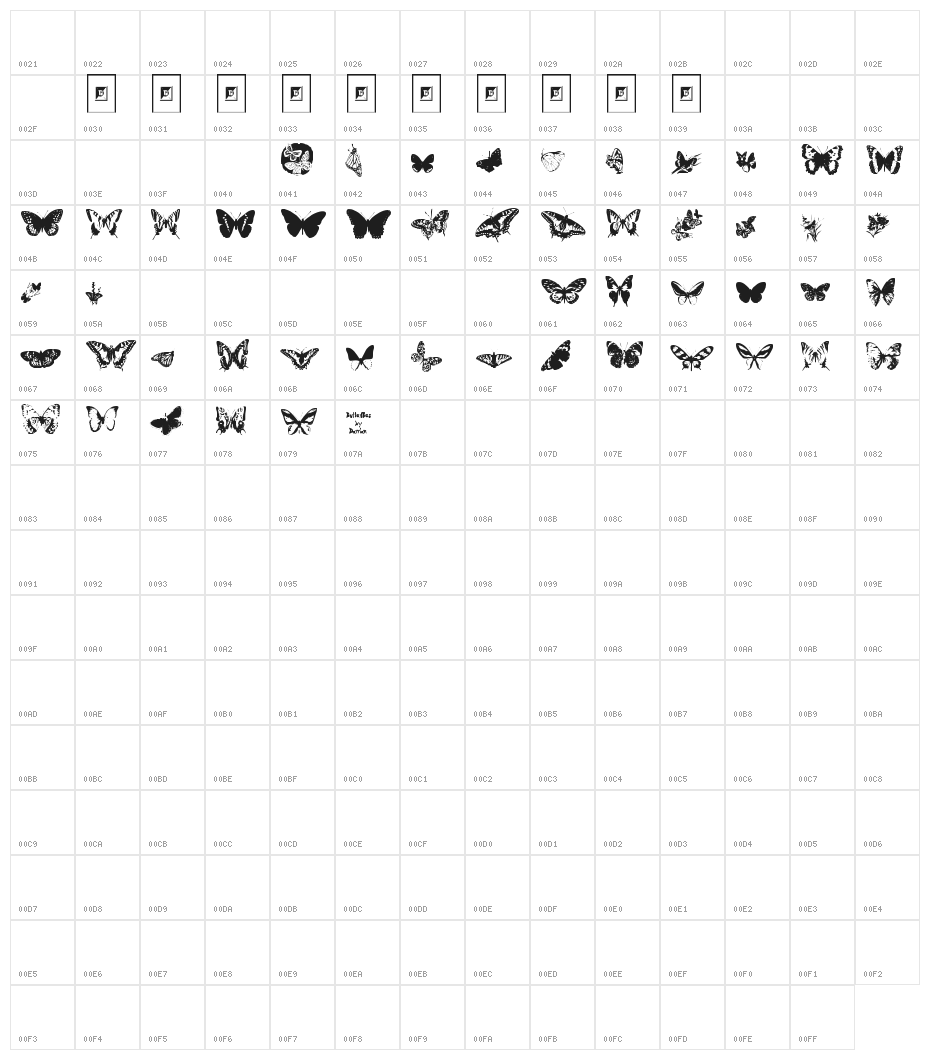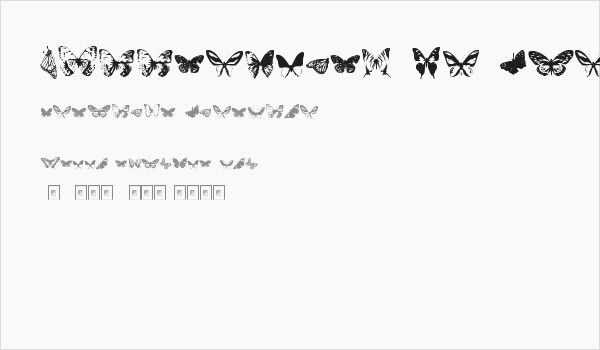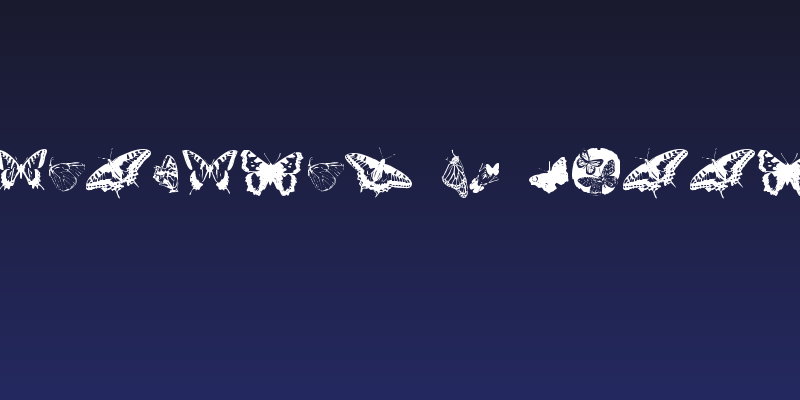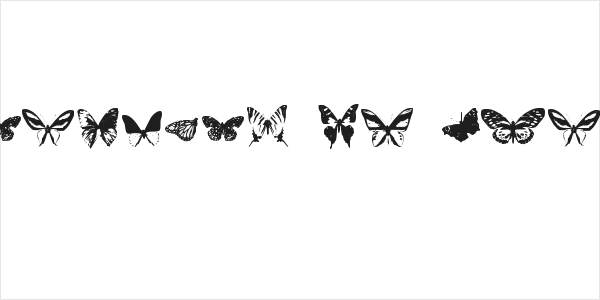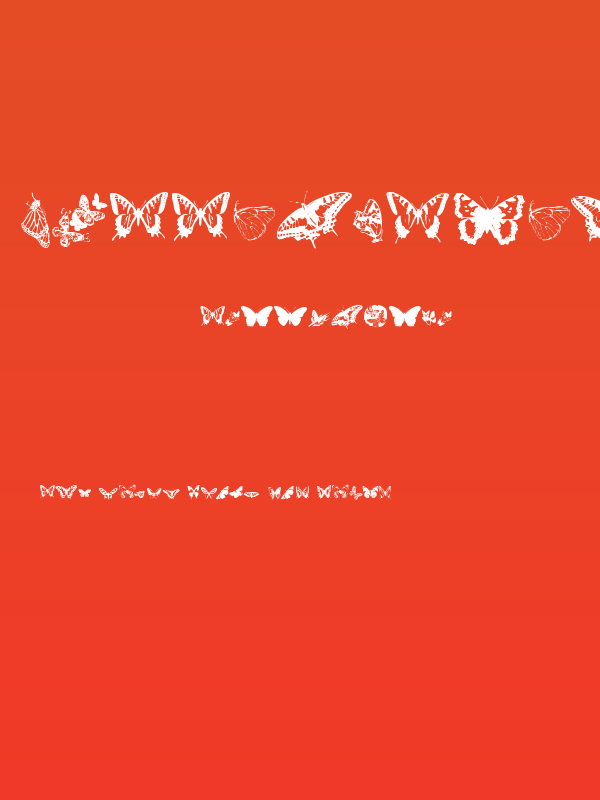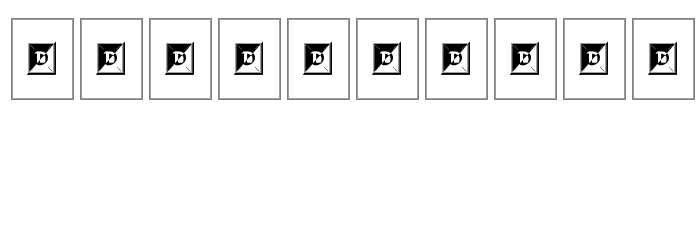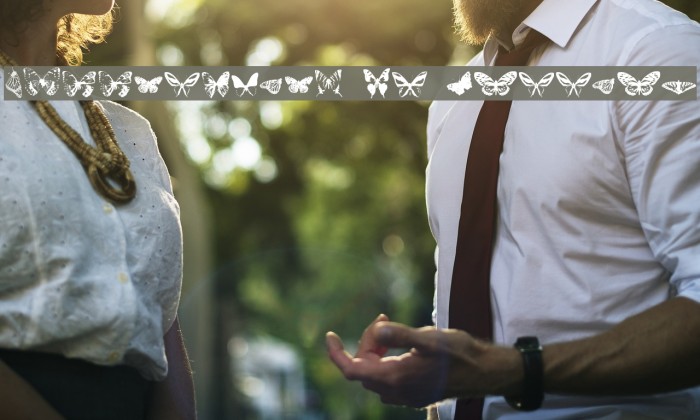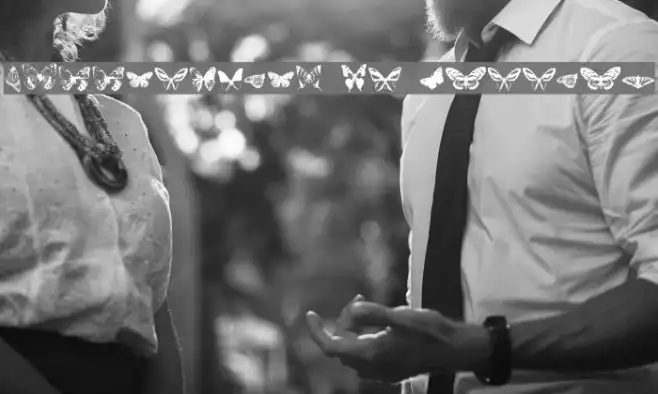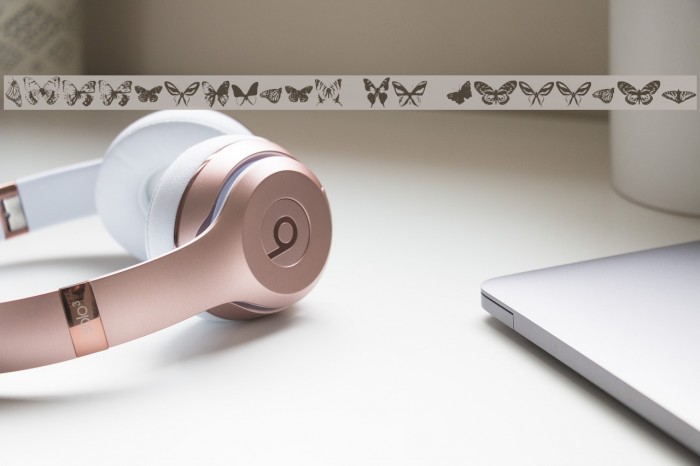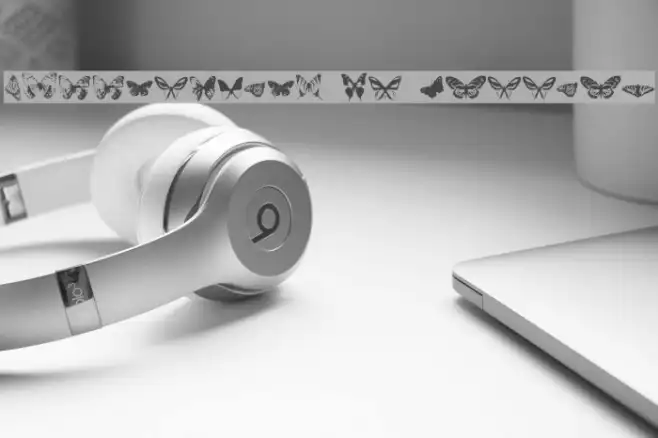
Butterflies by Darrian Font
Cette police comprend 66 caractères. Cliquez sur un caractère pour voir les détails.
| Nom | Butterflies by Darrian |
| Poids | Ultra-expanded |
| Catégories | Images & Symbols |
| Style général | Decorative, Nature-inspired |
| Cas d'utilisation | Logos, Headlines, Posters, Crafts |
| Projets proposés | Nature-themed posters, scrapbooking, invitations, branding for florists or environmental organizations, decorative headings. |